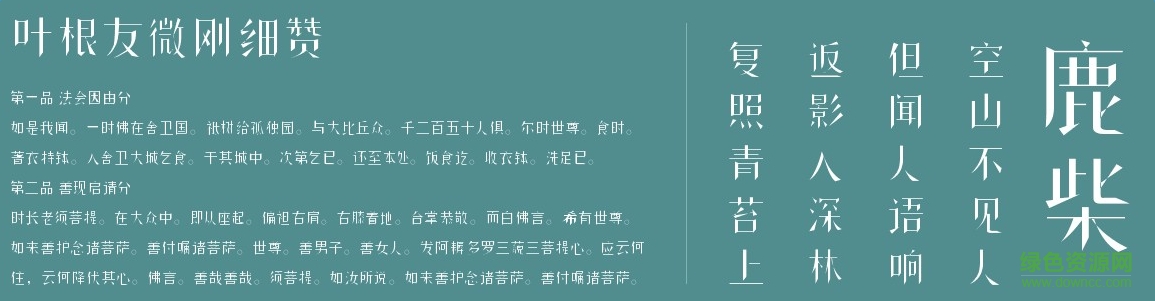
葉根友微剛細贊字體是一款由知名書法家葉根友創(chuàng)造的字體,適用于、字體排版、印刷等方面,有需要的朋友們不要錯過了。小編為大家提供免費下載地址。歡迎大家來綠色資源網(wǎng)踴躍下載哦!
葉根友微剛細贊字體,2016年度最新發(fā)布的字體,該字體風(fēng)格獨特,簡單大方而有銳氣,設(shè)計的理念來自竹林里砍竹子后的斜切面創(chuàng)意,利用這個創(chuàng)意應(yīng)用在書法字體上,形成了較好的體現(xiàn)效果。
葉根友微剛細贊字體,用途廣泛,是葉根友先生的印刷字體,字體非常纖細,適用于文字排版等方面。各位字體收藏者可以來看看。